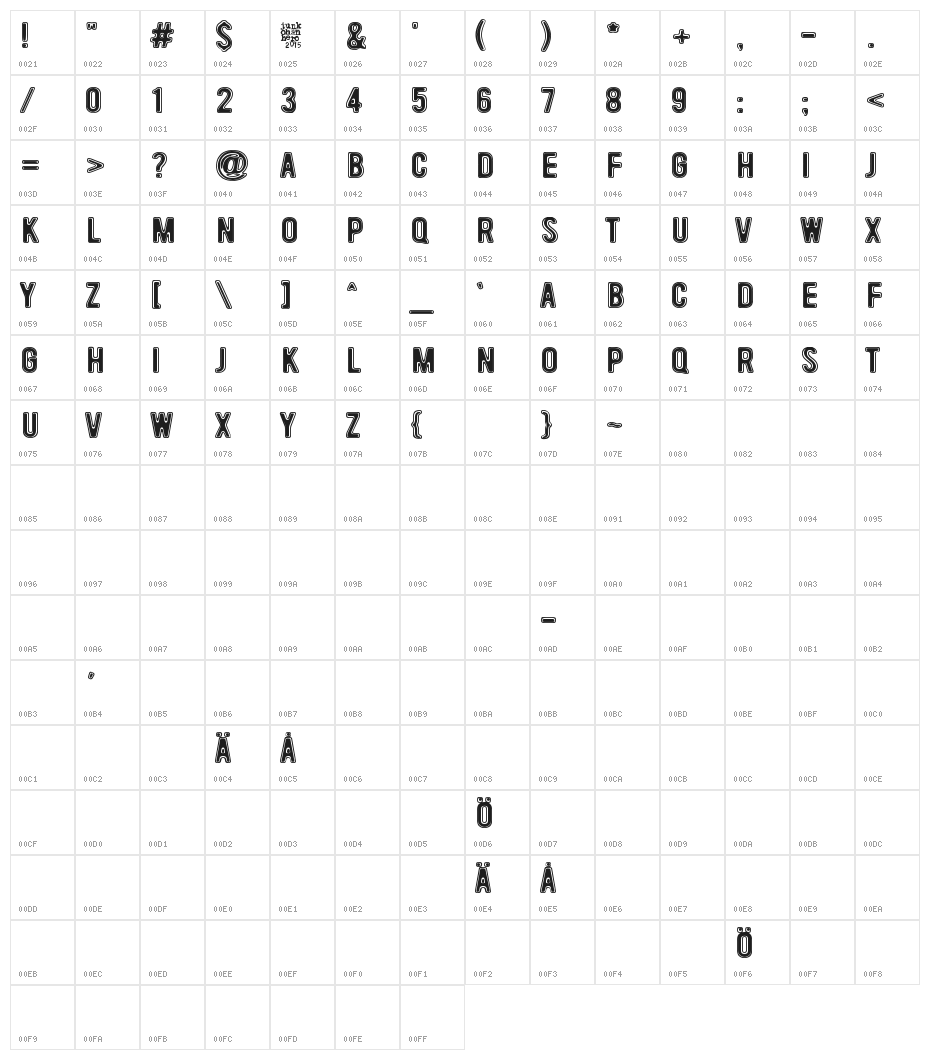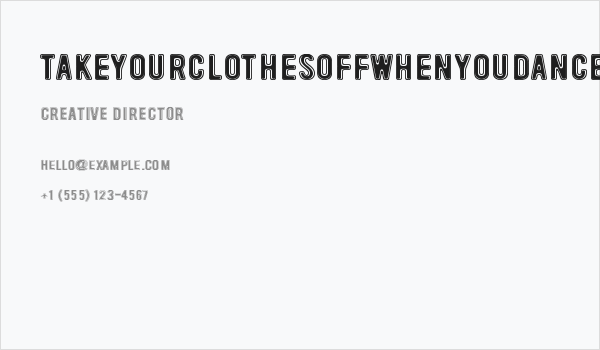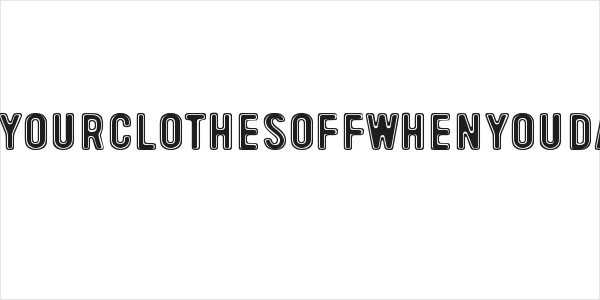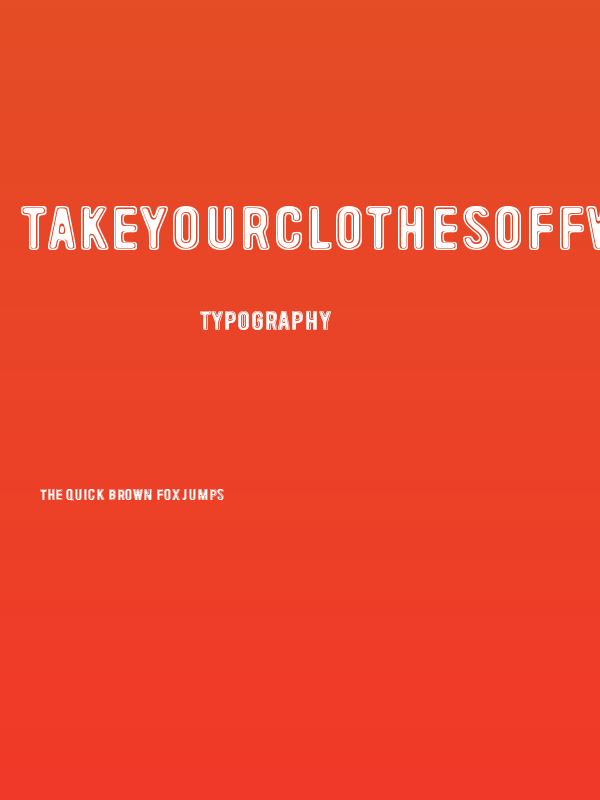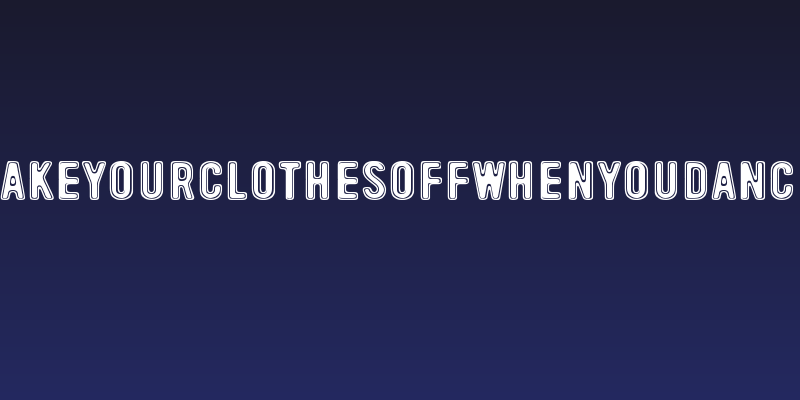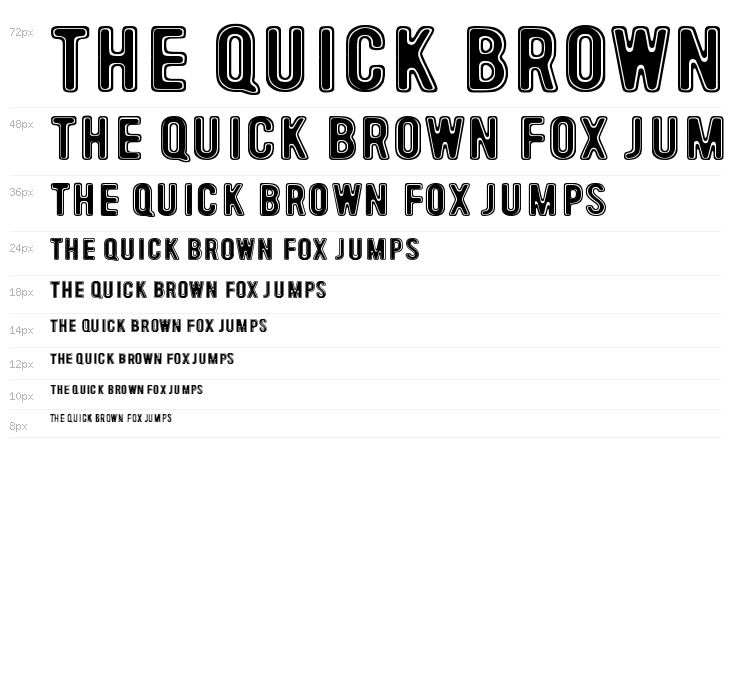
TakeYourClothesOffWhenYouDance Font
| Stile generale | Playful, Modern |
| Progetti proposti | Ideal for posters, event flyers, children's book covers, and playful branding projects. |